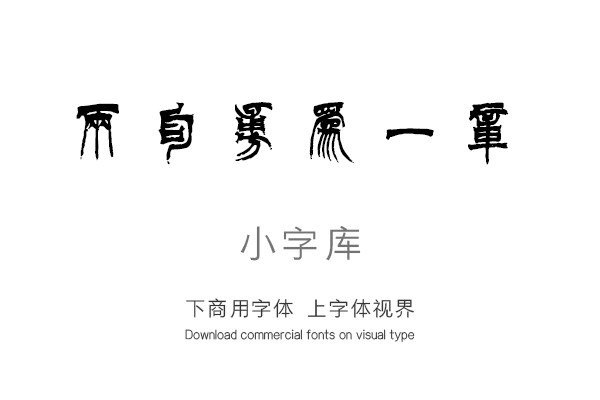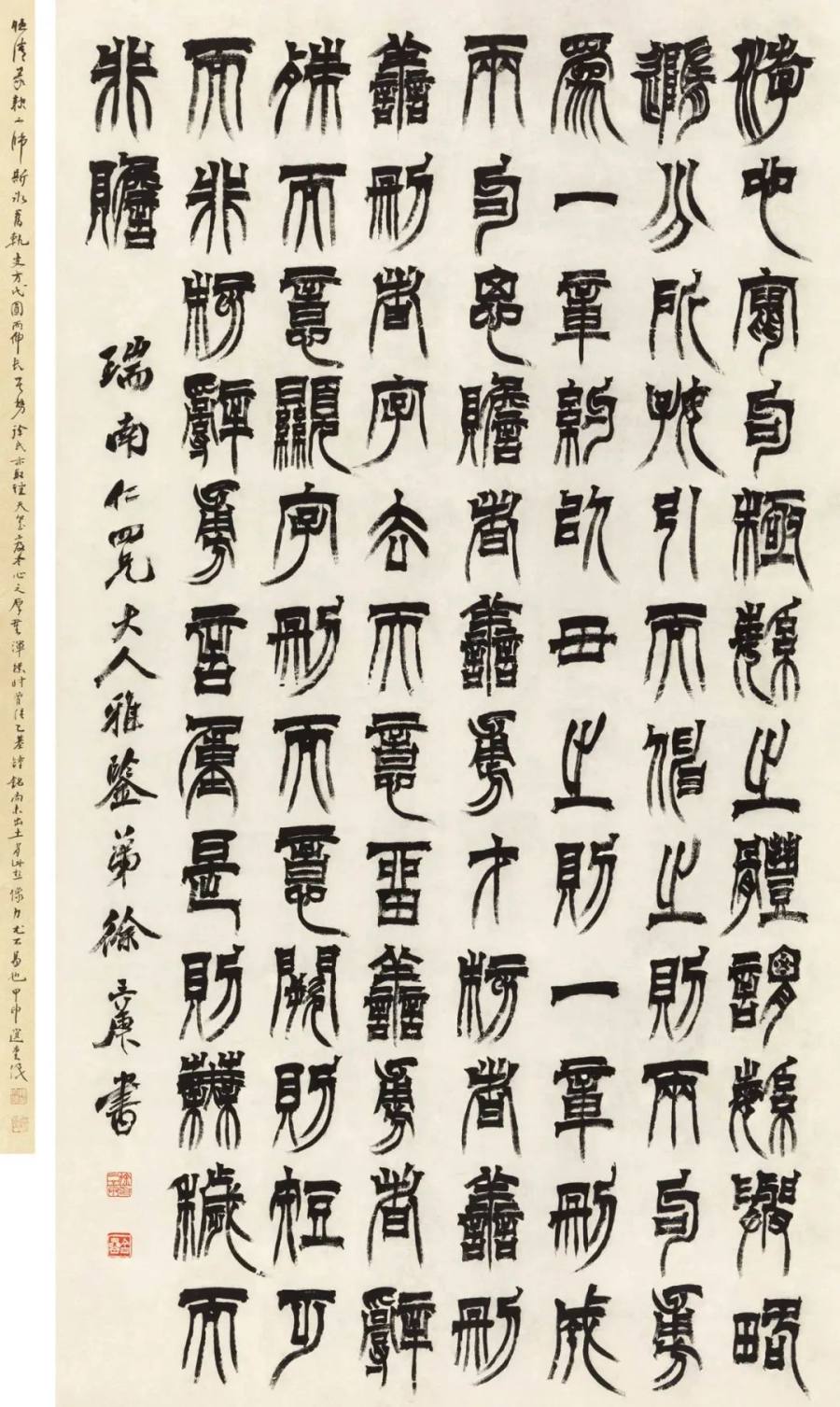
汉标徐三庚文心雕龙
《汉标徐三庚文心雕龙》是一款根据清代徐三庚《文心雕龙》,经过再次调整制作的小字库,该小字库共收录了该真迹作品中约117个字体。
游心窜句,极繁之体,谓繁与略,随分所好,引而伸之,则两句敷为一章,约以贯之,则一章删成两句,思赡者善敷,才核者善删,善删者字去而意留,善敷者辞殊而意显,字删而意阙,则短乏而非核,辞敷言重,是则芜秽而非赡。瑞南四兄大人雅鉴,弟徐三庚书。